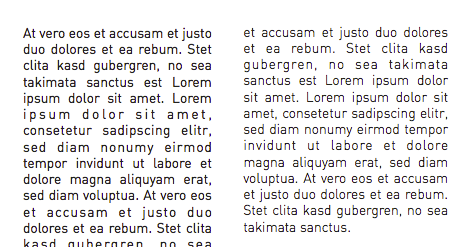
Welche (Serifen)-Headline-Schrift passt zu der DIN?
Jedenfalls. Ich schreibe gerade an einem Tutorialbuch, mit vielen Bildern und Marginalspalten und allem drum und dran. Für den Fließtext habe ich mich mit meinen Freundinnen schon beraten, die auch KD studieren und uns nach einem langen Für und Wider für die DIN entschieden. Jetzt suchen wir eine passende Headline Schriftart aber irgendwie ist alles entweder zu Zeitungs-, Magazinartig (Bodoni) oder zu langweilig oder schon zu sehr Spaßschrift...
Die Ansprüche an diese Headline Schriftart ist, dass sie Serifen hat und schon gern in die klassische Richtung gehen kann da das Thema des Buches u.a. das alte Galiläa und orientalischen Tanz beinhaltet, aber halt nicht zuuuuu verschnörkelt (im Grunde geht es darum wie man einen Spielecharacter in 3D baut aber dieser Charakter ist die Figur Salome, die ihren Stiefvater vor tausenden Jahren mit ihrem Tanz der sieben Schleier verführte)
Es ist also ein sehr technisches Buch, jedoch mit nem Designanspruch.
Die MRS EAVES geht auf jedenfall schon in die richtige Richtung!  Vllt muss man auch irgendwie mit den Überschriften spielen damit es "etwas besonderes" wird!?
Ich wollte gern den Fließtext serifenlos lassen, weil es dem ganzen einen Gegensatz bietet, da das Buch zB eine sehr klassische und verspielte Dublüre und einen Goldschnitt bekommt. Ich habe es mit Serifen versucht, aber das wirkt mir zu aufgesetzt mittelalterlich. Ich mochte diese Neo-Wirkung an der DIN.
Dafür darf ja dann aber die Überschrift auch wieder nostalgischer sein!
Es werden keine riesigen Fließtexte sein, eher viele Absätze, da es sone Art Step-by-Step-Anleitung wird. Ab und zu vielleicht mal was längeres... finde aber die DIN sehr gut lesbar ohne Anstrengung.
Also Entweder die DIN LightAlternate oder RegularAlternate...
Die MRS EAVES geht auf jedenfall schon in die richtige Richtung!  Vllt muss man auch irgendwie mit den Überschriften spielen damit es "etwas besonderes" wird!?
sie ist doch schon verspielt ;)
Welche DIN eigentlich genau?
Es gibt die gute alte DIN 1451 – die von den Straßenschildern. Da gibt es ein paar kostenlose Downloads, aber fließtextgeeignet ist die nicht.
Dann gibt es die professionell ausgebauten Familien FF DIN von FontShop, die DIN Next von Linotype sowie die PF DIN von Parachute. Mit denen kann man auch bedingt Fließtexte setzen.
Was im Netz als »DIN LightAlternate« und ähnliches herumfliegt, sind schlicht illegale Versionen der obigen, professionellen Varianten.
die DIN 1451 hab ich auch, die ist es nicht. Wüsste ich auch gern, welche der Sorten es dann ist, jedenfalls ist sie ebenfalls free.. Oder was meinst du mit illegal, darf man sie dann nicht benutzen?
Aber sie sieht aus wie oben auf dem Screenshot, bei meinem zweiten Beitrag.
Big Caslon wäre jetzt ebenfalls in meiner engeren Wahl....was sagt ihr?
ooooder Perpetua Titling!?
Kein Vorschlag zur Schrift, aber: Bitte die Sperrung im Fließtext ausschalten. Wir sind hier glücklicherweise nicht in Amerika und hierzulande dient Sperrung nicht dem Randausgleich, sondern ist eine Hervorhebung. Und Überschriften werden von Laien zwar gerne zentriert gesetzt, weil sie meinen, das gehört sich so. Aber meistens ist es linksbündig besser.
keine Sorge, ist doch nur zum gucken!
hier übrigens ein wunderschönes Layout-Beispiel wo auch zentrierte Überschriften toll aussehen.
Regeln(im Graphik Design) sind dazu da gebrochen zu werden, WENN man sie verstanden hat.
Hi Pauline : )
Ich finde auch, dass Mrs. Eaves recht gut zum Thema passt, auch besser als Caslon, Garamond etc.
Ihr könntet Euch als Alternative auch mal noch die Baskerville ansehen. Die hat verspielte Ziffern, denen man evtl. auch so etwas wie einen »orientalischen Touch« unterstellen könnte. Vorteil: Wenn Ihr mit Mac OS X arbeitet, sollte auch die Lizens klar gehen.
Falls Du noch unsicher bist, welche DIN-Version es letztendlich werden soll: Zu den unterschiedlichen DINs findest Du beispielsweise hier Hintergründiges:
Schade, eigentlich wollte ich hier auf den recht aufschlussreichen Vergleich auf Typolution.de linken, aber der scheint wohl nicht mehr zu existieren …
Wir sind hier glücklicherweise nicht in Amerika
:tuschel:  Hinweise auf landestypische Gepflogenheiten lassen sich doch sicherlich auch ohne solche Polemisierungen geben. :huhu:
Naja, das mit dem »glücklicherweise« empfinde ich in typografischer Hinsicht wirklich so. Wobei: Wenn ich darüber nachdenke, sollte ich das doch etwas relativieren. Zwar ist für mich die Sperrung zum Randausgleich tatsächlich eine Verfehlung, weil sie im Seitenbild stört. Und mit den langen Strichen, die da stehen, wo wir einen Gedankenstrich machen, und die dann noch dazu ohne Leerzeichen davor und danach gesetzt werden und die deshalb ja eigentlich eher eine Verbindung darstellen als dass sie einen Einschub absetzen würden, kann ich genauso wenig anfangen. Auch den doppelten Leerzeichenabstand nach einem Punkt finde ich fragwürdig. Dafür könnte ich mich vielleicht mit den amerikanischen Anführungszeichen anfreunden, weil ich sie eigentlich für stimmiger halte als die deutschen Gänsefüßchen (warum müssen die am Anfang unten und am Schluss oben sein?).
Zum geschichtlichen Thema paßt das natürlich nicht besonders. Ich würde deshalb eher eine kalligraphisch-altertümliche Schrift für die Überschriften und dazu passend eine dynamische Grotesk für den Text benutzen. Etwas in der Richtung:
Alcuin wäre aber sehr holzhammermäßig. Ich finde nach wie vor eine o. ä. Caslon am besten, auch Baskerville fände ich zu langweilig.